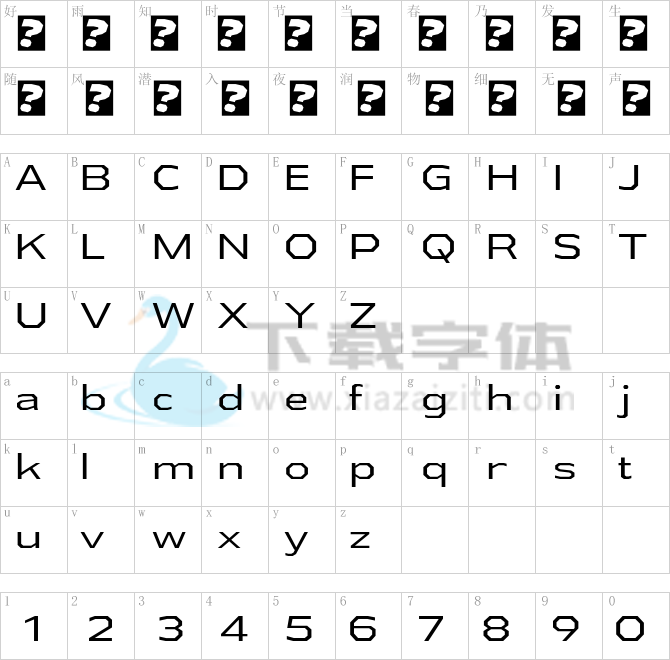
Athabasca Ex Bk.ttf字体下载
Athabasca Ex Bk.ttf字体下载,这款字体结构工整、笔画清晰,兼顾美观与易读性,适用于标题、正文、海报、包装、LOGO 等多种场景。字形优雅稳定,风格百搭耐看,适配日常排版与创意设计,让文字呈现更舒适、更具质感。Athabasca Ex Bk.ttf字体下载一笔一画,皆是细节,以均衡的比例、流畅的线条打造舒适视觉体验,字形端正大气,风格简约现代。无论是商业设计、品牌宣传还是日常排版,都能轻松驾驭,让文字更有格调与力量。Athabasca Ex Bk.ttf字体下载字体下载。
Athabasca Ex Bk.ttf图片展示
• 字体名称:Athabasca Ex Bk